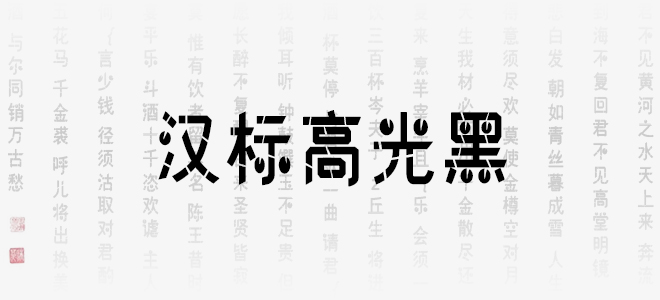
漢標(biāo)高光黑字體是根據(jù)黑體的字形創(chuàng)作而來,作者通過大量裁剪設(shè)計字形,使得字體有撕裂感,從而展現(xiàn)美術(shù)視覺的高光感,蘊含著深沉的藝術(shù)魅力,能給人以無限的美感,適合應(yīng)用于藝術(shù)設(shè)計、平面宣傳、包裝印刷、圖形設(shè)計、網(wǎng)頁設(shè)計、書法字帖等領(lǐng)域。歡迎喜歡漢標(biāo)高光黑字體的朋友前來下載使用。
漢標(biāo)高光黑